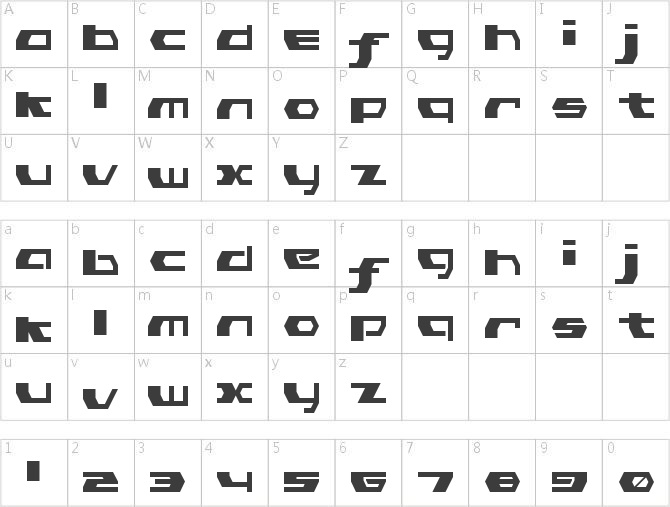
pink_has_gone_extinct_regular 詳情頁
pink_has_gone_extinct_regular
pink_has_gone_extinct_regular介紹
pink_has_gone_extinct_regular字體字庫是一款讓人賞心悅目、百看不厭的英文字體,適合各類廣告和產品包裝設計應用,字體大小0.01MB,格式為ttf字體,上傳用戶是M_墨董,作者/版權方為未知
pink_has_gone_extinct_regular效果圖